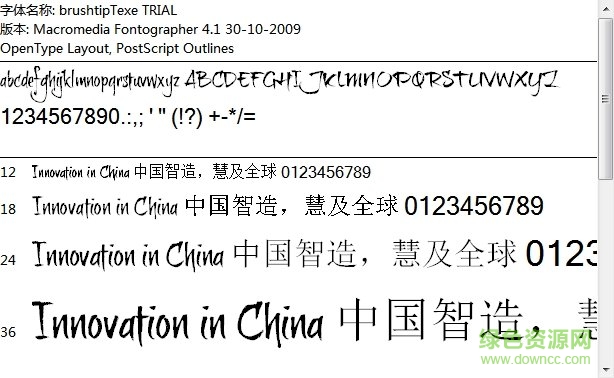
brushtiptexetrial字體是一款流暢大氣的英文字體,極具英文書法字體的飄逸飄逸運維,讓文字曲線優(yōu)美,更加生動好看,快來綠色資源網(wǎng)試試吧!
brushtip texe trial字體兼具手寫字體和毛筆字體的風(fēng)格,行文流暢而精簡,讓文字倍顯清晰自然,中文上無較多處理,可以在平面設(shè)計、海報設(shè)計、包裝設(shè)計、廣告設(shè)計等領(lǐng)域使用!
brushtip texe系列字體包括brushtipTexeTRIAL Regular、brushtipTexe Regular和brushtipTexe,風(fēng)格上比較接近,但brushtiptexetrial字庫更加完整,可以滿足日常工作學(xué)習(xí)的需要!